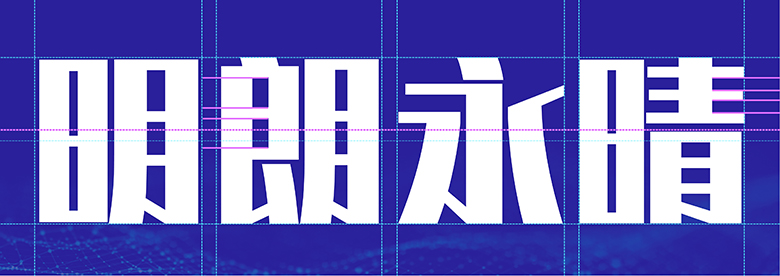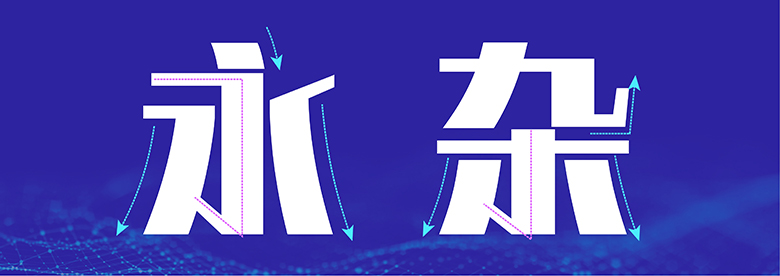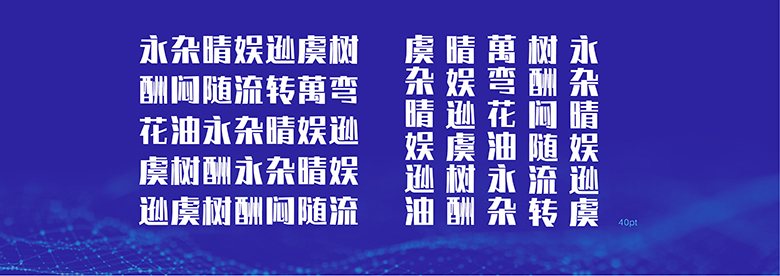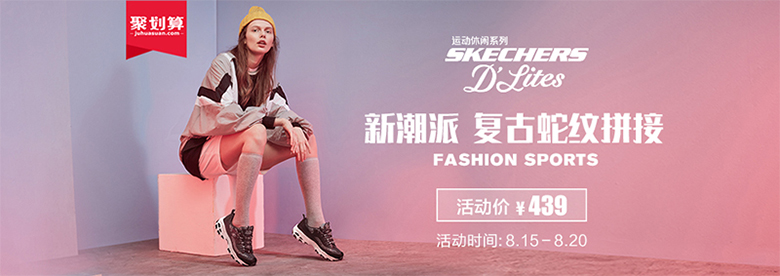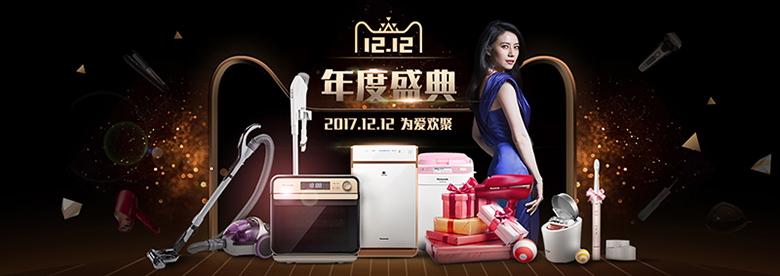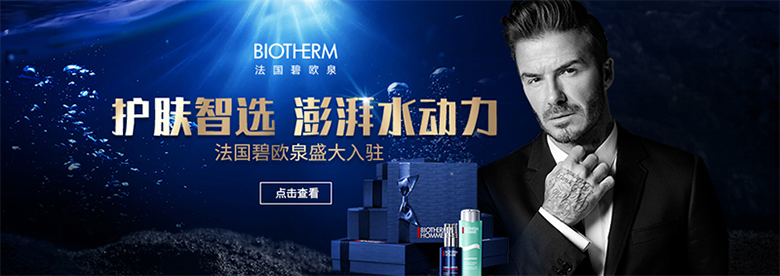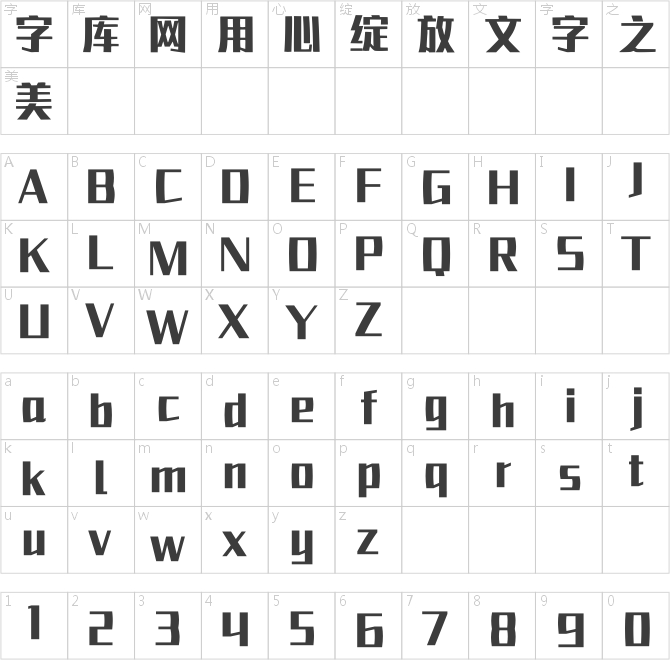
阿里漢儀智能黑體 詳情頁
阿里漢儀智能黑體
阿里漢儀智能黑體介紹
今天,人工智能將字體帶入了一個新的世界!
漢儀字庫聯手阿里巴巴
打造的第一款AI字體產品
阿里漢儀智能黑體Beta
正式上線!
科技,讓設計回歸創意
人工智能持續升溫,
我們能為行業做哪些貢獻呢?
人工智能踏足字體設計領域,將幫助設計師解決大量重復性工作的問題,提升效率,讓設計回歸創意,創造出更多的社會價值。
這套字體的beta版本已正式上線并提供給阿里巴巴平臺用戶使用,最終字符集為6763,將在2018年4月份正式發布。
阿里漢儀智能黑體
字形主創設計師
中文 | 黃珍元    西文 | 黃永輝
人工智能字庫生成
人工智能技術專家 | 森飔
參與訓機設計師
盧鑫亞  李曉靜 趙鈺 奚望 胡萌 羅夢怡 滕侍茜 張小玉 譚曉 孔千燁 韓公正
漢儀字庫技術支持
靳俊
字符集信息
包含GB2312-80標準中3500個常用中西文字符
(Beta版)
符合GB2312-80標準的6763個中西文字符
(正式版)
阿里漢儀智能黑體,字形由漢儀字庫的字體設計師黃珍元主創設計,字庫產品協同阿里人機自然交互實驗室,通過
強大的計算能力自學生成。這款字體是基于阿里巴巴電商平臺應用場景下產生的新分類字體 —— 電商字體。
作為漢儀字庫與阿里合作的第一款電商字體的代表,智能黑體具有強烈的對話性特征。智能黑體基于黑體的橫豎基本特征,加大
橫豎粗細比例,字面飽滿填充整個內框,讓字體更加醒目,視覺沖擊力極強,能夠很好的與用戶對話,非常適用于電商類廣告設計。
電商字體通用性極強,適用于絕大多數品類的商品。智能黑體區別于常規黑體,剛中帶柔,筆畫的走勢上融入了手寫的方式,整體
方正但又不失趣味,度量把握適中。
電商字體的使用受限于自身的傳達介質 —— 屏幕顯示,字體使用大小也受限于廣告設計的尺寸,因此這類字體的生成
有別于傳統字庫的精細程度,力求既滿足電商設計的辨識度及美觀程度,同時又能保證人機協作快速生成字體的效率。
官方通過大量比對網頁廣告中的文字使用情況,目前完成的阿里漢儀智能黑體將適用于完成網頁圖片中128px以下的標題字使用。
電商字體還應該具備哪些特質呢?
電商字體,顧名思義是基于電商平臺展示開發的字體,是服務于電商平臺場景下的設計展示所需要的字體,例如廣告banner等。
(阿里漢儀智能黑體使用案例,由寶尊電商設計提供)
除了具備強烈的對話性通用性之外,電商字體將更加高效的解決電商類平臺的用字需求,
由于其自身獨特的屬性,電商字體的開發將會瞄準高頻小字符集的需求。
(阿里漢儀智能黑體使用案例,由寶尊電商設計提供)
電商字體也不再拘泥于傳統的黑宋仿楷分類模式,讓產品分類更加多樣化標簽化(少女字體、兒童字體、運動字體等),阿
里巴巴作為中國最大的電商平臺,擁有非常廣泛的消費品種類,相應的也需要多樣化的電商字體來匹配多品類的場景,而這背后所
依托的也正是漢儀字庫強大的專業字體設計能力與龐大豐富的產品積累。
人工智能字體到底是如何生成的呢?
阿里漢儀智能黑體由阿里計算平臺事業部PAI產品線Deep Learning團隊與阿里人機自然交互實驗室以及漢儀字庫設計師協作完成。
這款字體的生成是人機協同工作的成果,機器學習,人工干預,循環往復,直到最終生成達標字庫的一個過程。
人機協同的過程中,設計師的工作是極其重要并且無法替代的,包括前期字形創意提供以及生成過程中對于機器的訓練。